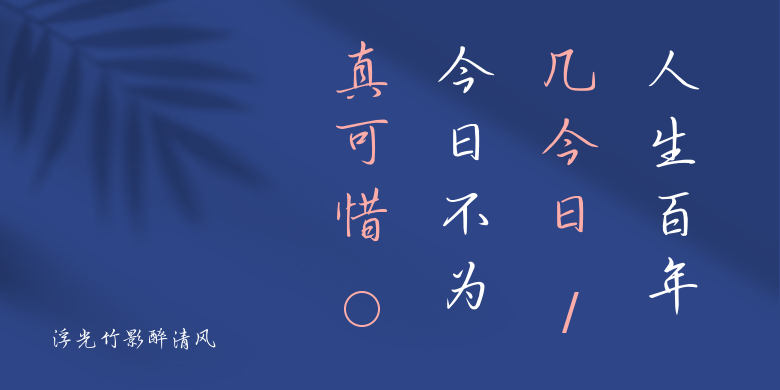
浮光竹影醉清风
浮光竹影醉清风,这款字体结构工整、笔画清晰,兼顾美观与易读性,适用于标题、正文、海报、包装、LOGO 等多种场景。字形优雅稳定,风格百搭耐看,适配日常排版与创意设计,让文字呈现更舒适、更具质感。浮光竹影醉清风一笔一画,皆是细节,以均衡的比例、流畅的线条打造舒适视觉体验,字形端正大气,风格简约现代。无论是商业设计、品牌宣传还是日常排版,都能轻松驾驭,让文字更有格调与力量。浮光竹影醉清风字体下载。